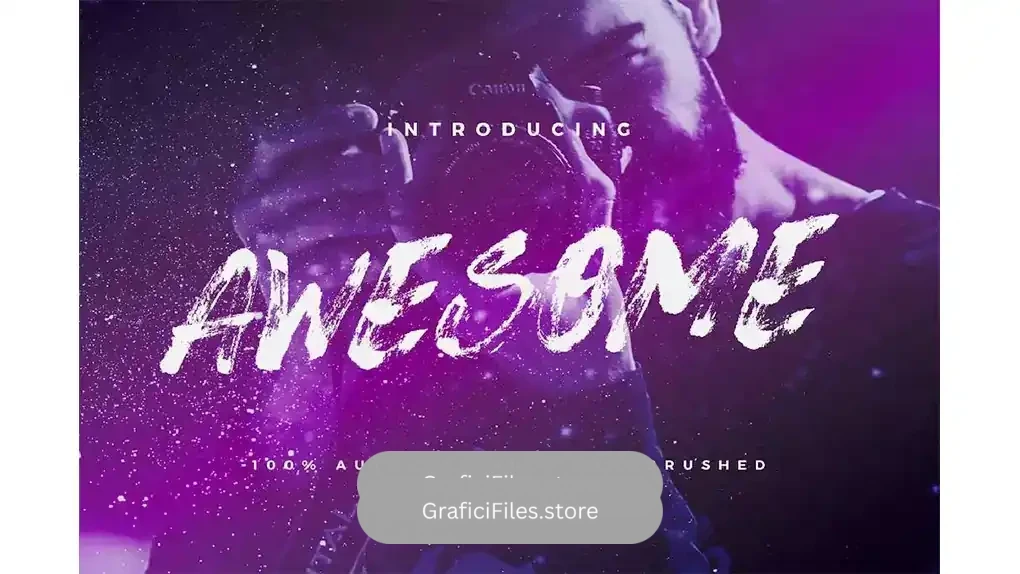
دانلود فونت انگلیسی دست نویس Awesome Typeface
فونت انگلیسی دست نویس Awesome Typeface : این مجموعه شامل یک فونت انگلیسی دست نویس است که برای تبلیغات، فروش، لوگو، برندینگ، پوستر، شبکه های اجتماعی و غیره مناسب میباشد.
فونت انگلیسی دست نویس Awesome Typeface - 1
فونت انگلیسی دست نویس Awesome Typeface - 3
فونت انگلیسی دست نویس Awesome Typeface - 5
فونت انگلیسی دست نویس Awesome Typeface - 7
فونت انگلیسی دست نویس Awesome Typeface - 9